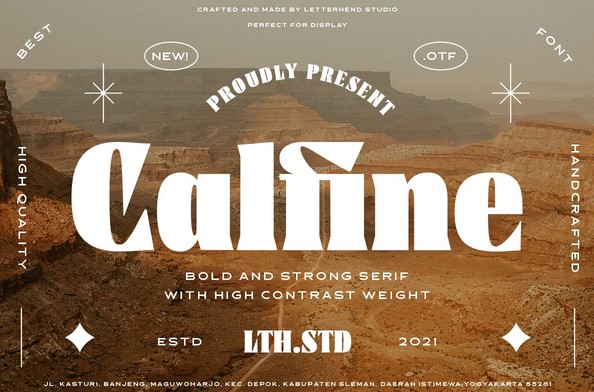
Creativemarket Calfine Font
[Creativemarket] Calfine Font
Calfine - это смелый, крутой, толстый шрифт с засечками.
Он имеет стильный, элегантный и современный вид, который можно использовать для логотипов, брендинга, приглашений, канцелярских принадлежностей, свадебных дизайнов, постов в социальных сетях и многого другого!